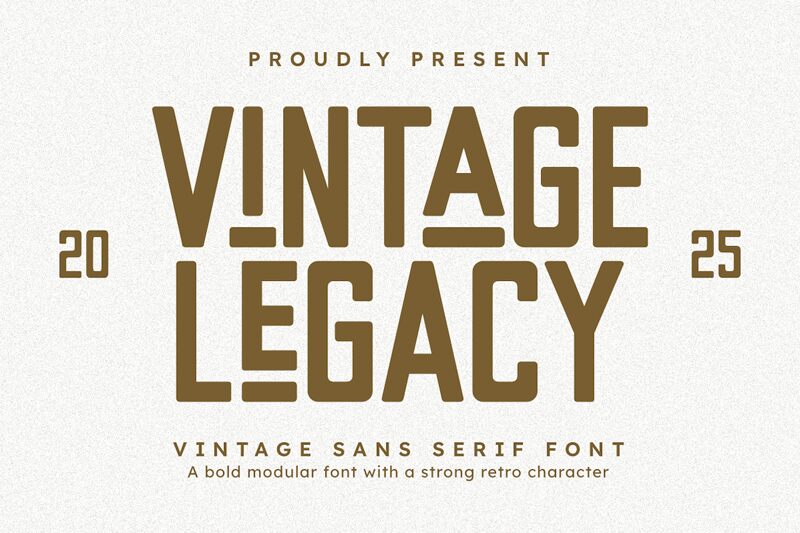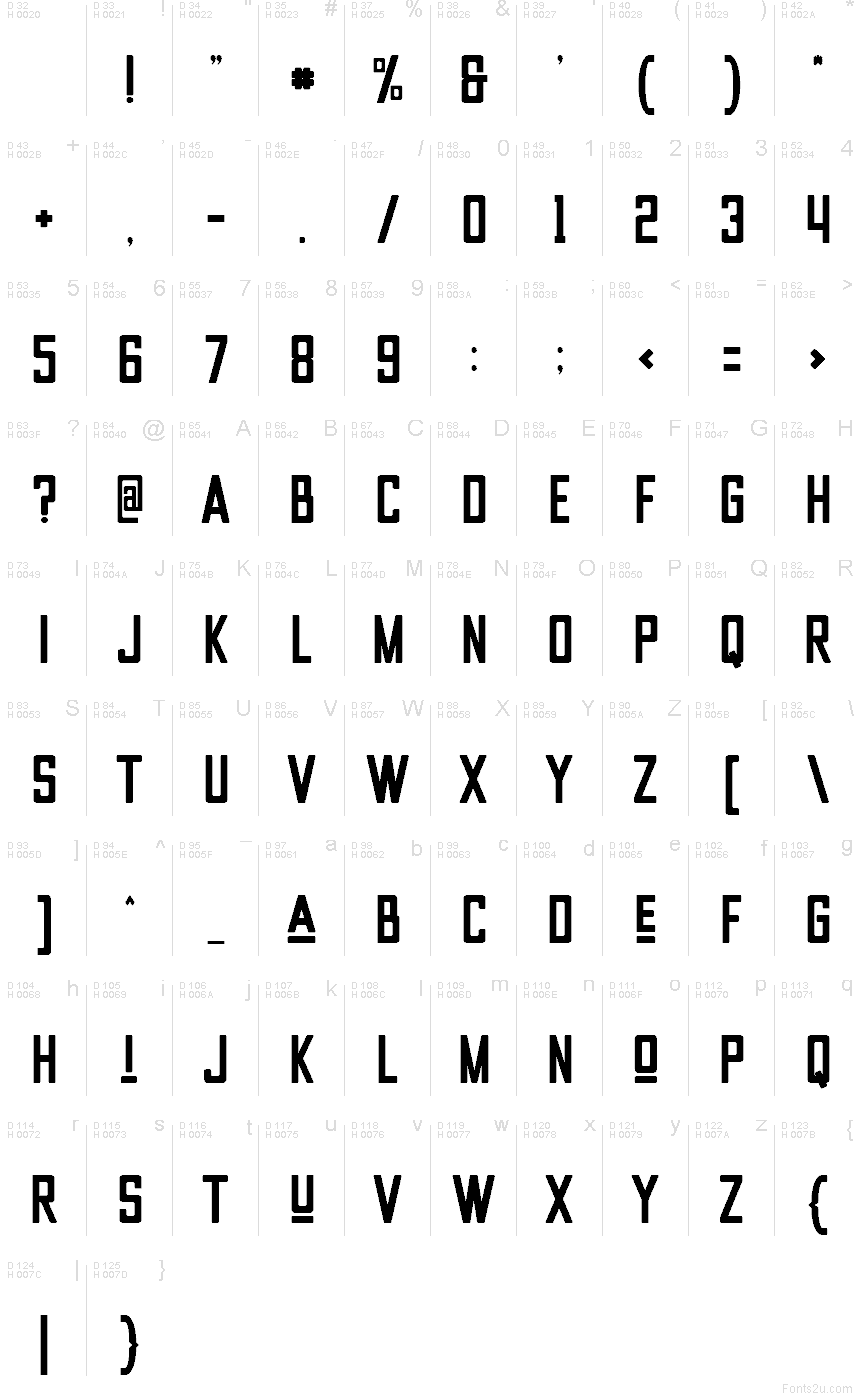
Vintage Legacy Regular
Vintage Legacy od Almairatype je bezplatné retro písmo typu display s vysokými, zúženými tvary písmen a výraznými blokovými tvary. Znaky využívají ploché hrany, ostré úhly a široké horizontální linky, které designu dodávají vzhled starých nápisů bez zbytečných příkras.
Vintage Legacy skvěle funguje na plakátech, obalech alb, retro obalech, logotypech i cedulích, protože jeho kompaktní struktura drží tvar v krátkých, úderných textech. Toto bezplatné písmo se hodí také pro grafiku akcí a titulky, pokud hledáte přímočarý styl s nádechem průmyslové historie.